Projekt Manual — časť 4: Kto navrhol uličné tabuľky?
Pátranie po pôvode dizajnu samotných uličných tabuliek. Kto a kedy ich navrhol? Bol ich dizajn štandardizovaný?
Keďže uličné tabuľky sú v podstate uniformné na celom území Slovenska, dalo by sa očakávať, že ich dizajn bude definovaný nejakou normou, štandardom alebo nariadením. Najstaršou zmienkou o označovaní ulíc a budov, ktorú sa mi podarilo nájsť, je vyhláška 97/1961 Ústredného úradu pre veci národných výborov zo 4. septembra 1961 o názvoch obcí, označovaní ulíc a číslovaní domov. Obsahuje informácie o umiestnení a obsahu tabuliek, nerieši však ich vzhľad. Táto vyhláška bola nahradená vyhláškou 93/1970 Ministerstva vnútra Slovenskej socialistickej republiky z 18. júna 1970 o určovaní názvov obcí a ich častí, ulíc a iných verejných priestranstiev a o číslovaní budov, ktorá bola doplnená o nasledovnú prílohu:
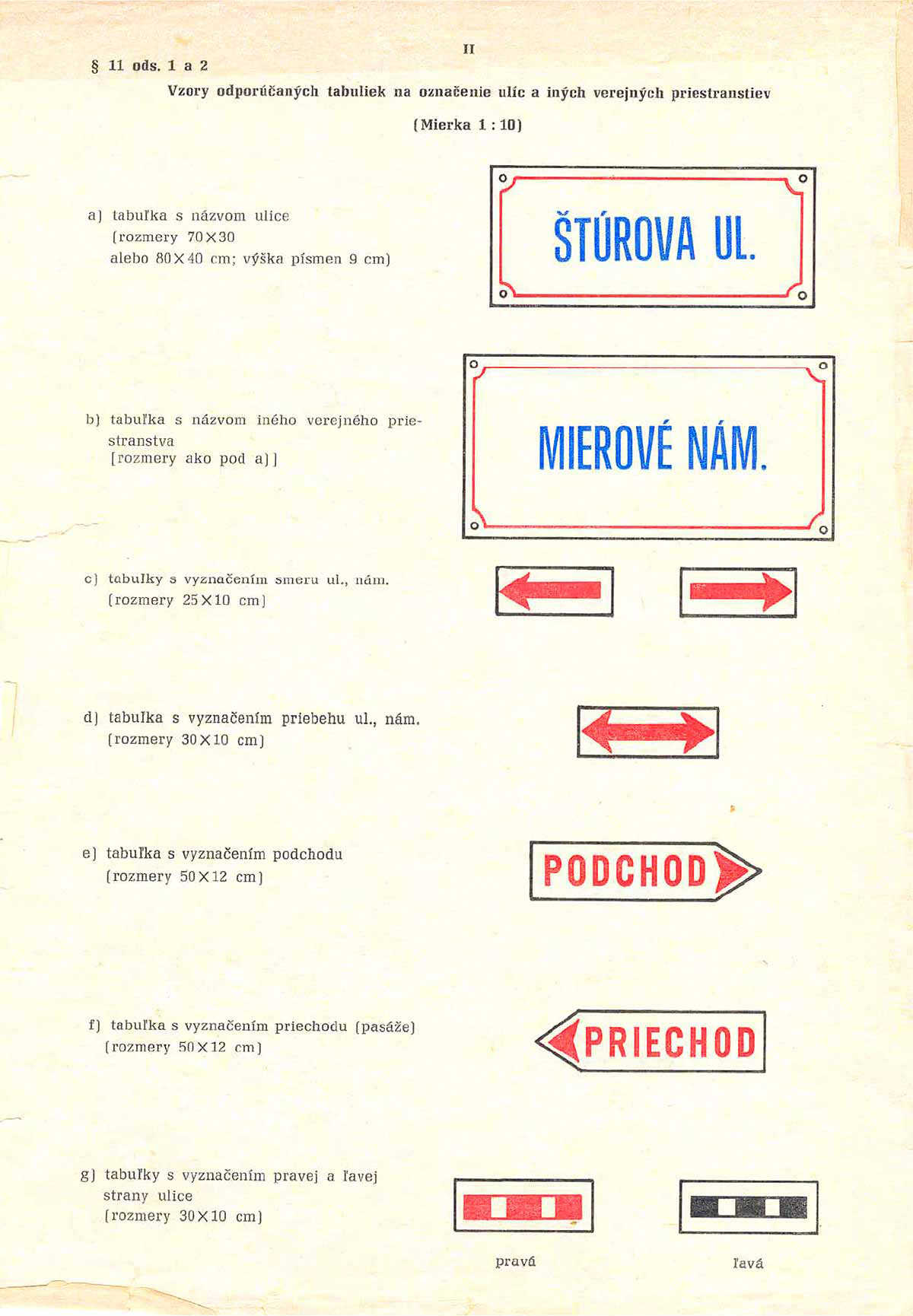
Ako môžeme vidieť, tento vzor obsahuje rozmery a layout tabuliek, vôbec však nerieši typ písma. Je prekvapivé, že hoci sa v roku 1970 uličné tabuľky s písmom Manual Grotesk už dávno vyrábali, vzor používa písmo, ktoré sa na reálnych tabuľkách nikdy nepoužívalo. S najväčšou pravdepodobnosťou ide o písmo, ktoré možno v publikáciách nájsť pod názvom Pražský Grotesk. Ako a kde tento vzor vznikol sa mi zistiť nepodarilo.
Vyhláška 93/1970 bola v účinnosti až do roku 1990, kedy bola nahradená zákonom 517/1990 Slovenskej národnej rady z 22. novembra 1990 o územnom a správnom členení Slovenskej republiky. Tento zákon už grafické vzory neobsahuje, pribudol však §8 odsek 4 s vetou “V každej obci možno používať orientačné tabule iba jedného vzoru.” Tak, ako pomenovania ulíc a ich označovanie, dizajn uličných tabúľ bol ponechaný na samosprávy.
V znení najaktuálnejšieho predpisu, ktorý pojednáva o označovaní ulíc – vyhláške 31/2003 Ministerstva vnútra Slovenskej republiky z 30. januára 2003, ktorou sa ustanovujú podrobnosti o označovaní ulíc a iných verejných priestranstiev a o číslovaní stavieb – k vete “Ulice sa označujú názvami na orientačných tabuliach rovnakého typu” pribudlo ešte “Tabuľka so súpisným číslom a tabuľka s orientačným číslom sa umiestňujú vedľa seba tak, aby boli z ulice dobre viditeľné a nepôsobili rušivo na vzhľad budovy.” To sú jediné zmienky o vzhľade.
Po prehľadaní zákonov som sa obrátil na databázu Úradu pre normalizáciu, metrológiu a skúšobníctvo Slovenskej republiky. Z obdobia začiatku druhej polovice 20. storočia existujú dve technické normy týkajúce sa písma, nanešťastie ani jedna z nich nerieši písmo uličných tabúľ.
Kde sa teda tento dizajn vzal? Ponúka sa jedno relatívne racionálne vysvetlenie. Uličné tabuľky, ktoré sa v súčasnosti používajú na Slovensku sa objavili začiatkom 50. rokov minulého storočia a vyrábali sa v štátnom podniku Kodreta Myjava. Kodreta produkovala tabuľky pre celé Slovensko, mala na ich výrobu prakticky monopol. Z rovnakého obdobia pochádza aj publikácia Richarda Pípala Písmo a jeho konstrukce, ktorá obsahuje najpodorobnejší popis konštrukcie písiem rodiny Manual Grotesk. Je teda celkom pravdepodobné, že dizajn aj písmo bolo jednoducho navrhnuté niektorým zo zodpovedných pracovníkov Kodrety, ktorý poznal a využil práve model Richarda Pípala. No a keďže tabuľky okrem štátneho podniku Kodreta nevyrábal nik iný, nebola ani potreba ich dizajn definovať v technickej norme alebo v zákone.